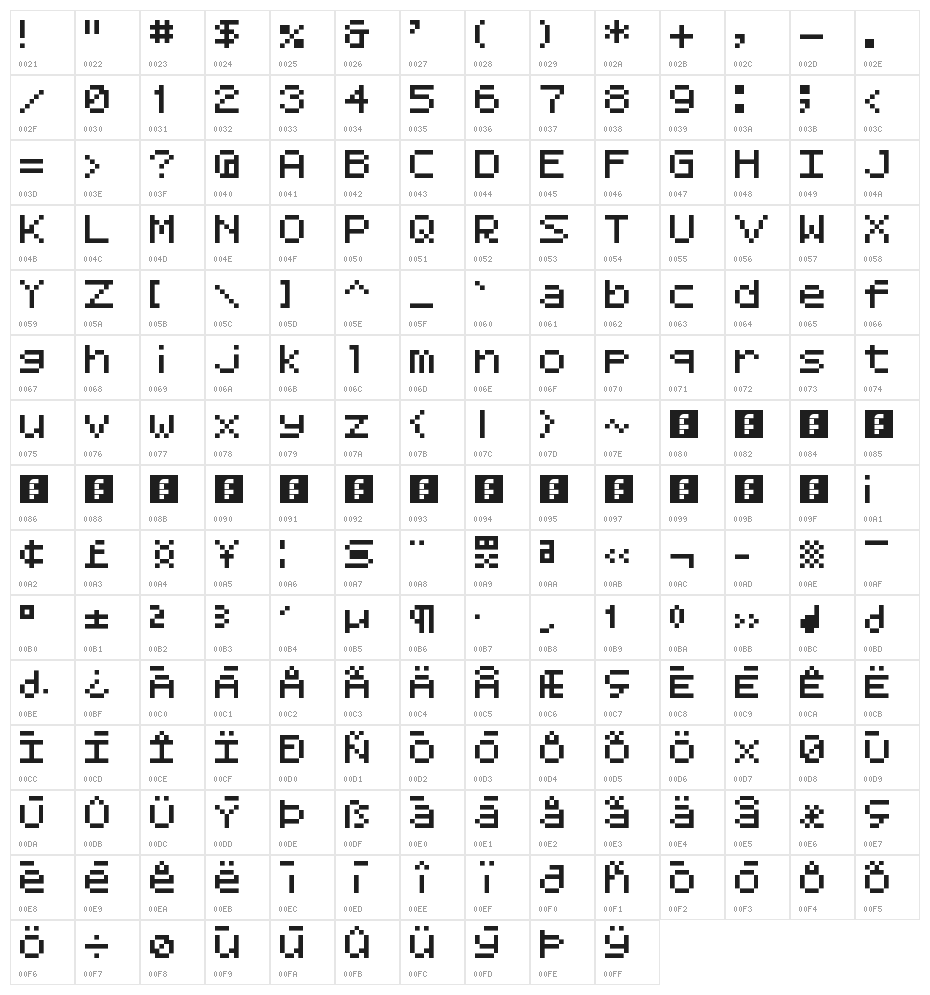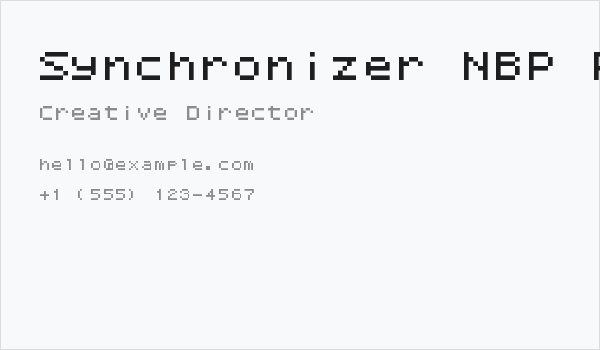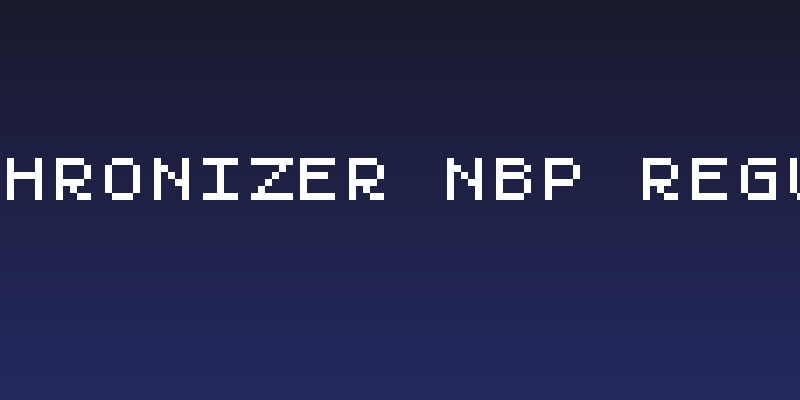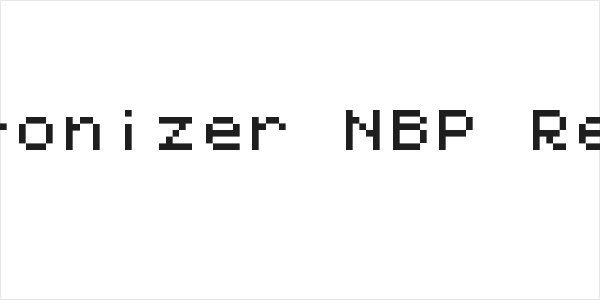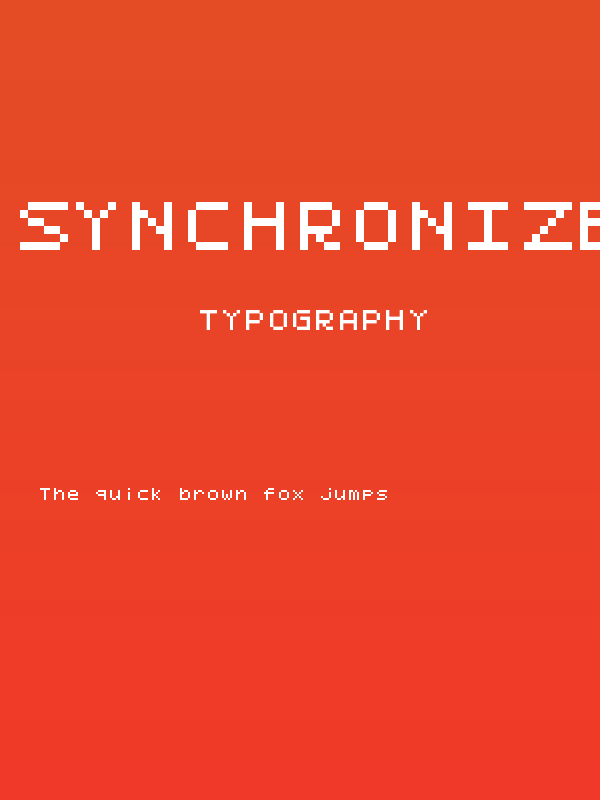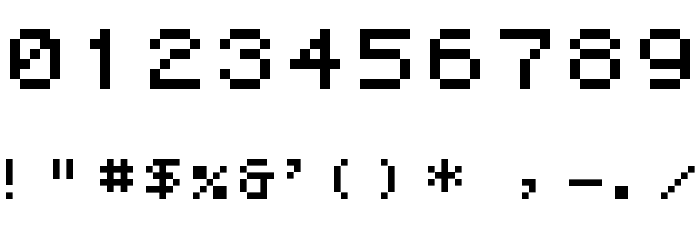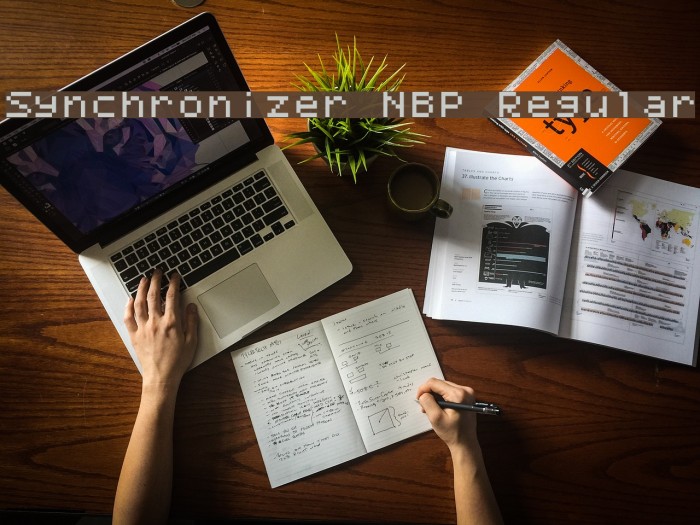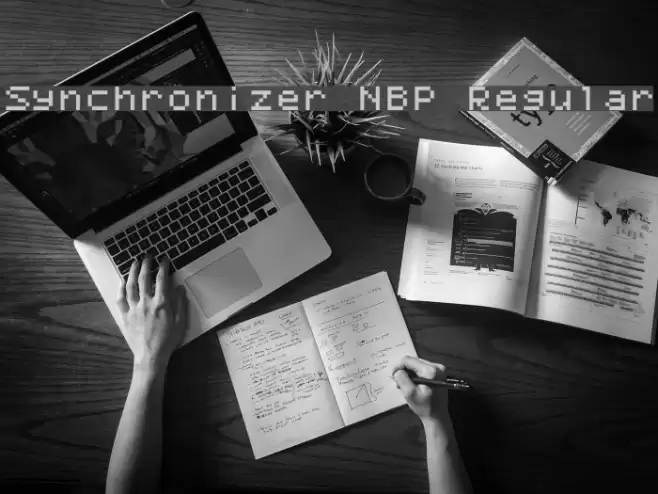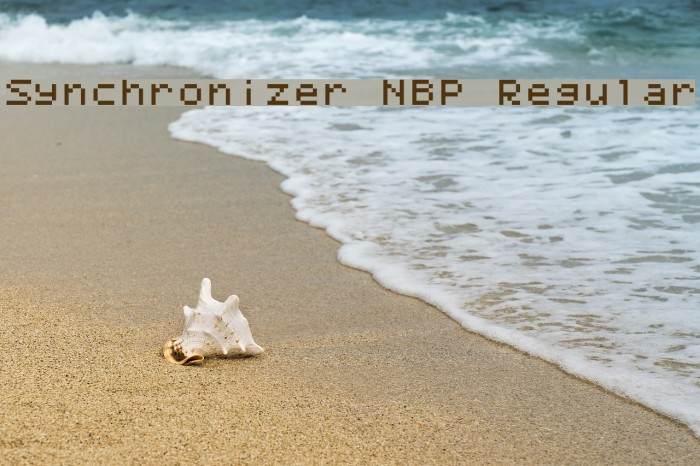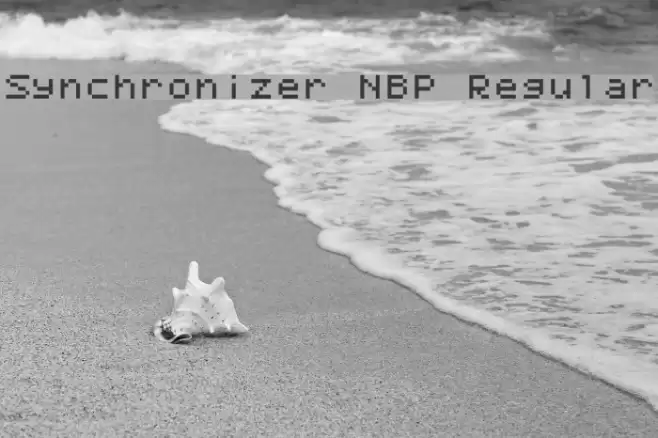
Synchronizer NBP Regular Font
| Estilo general | Vintage |
| Caso de uso | Logos, Digital displays, Retro-themed projects |
| Proyectos propuestos | Ideal for retro-themed designs, video game graphics, digital art projects, and any creative work that seeks to evoke nostalgia for early computing. |